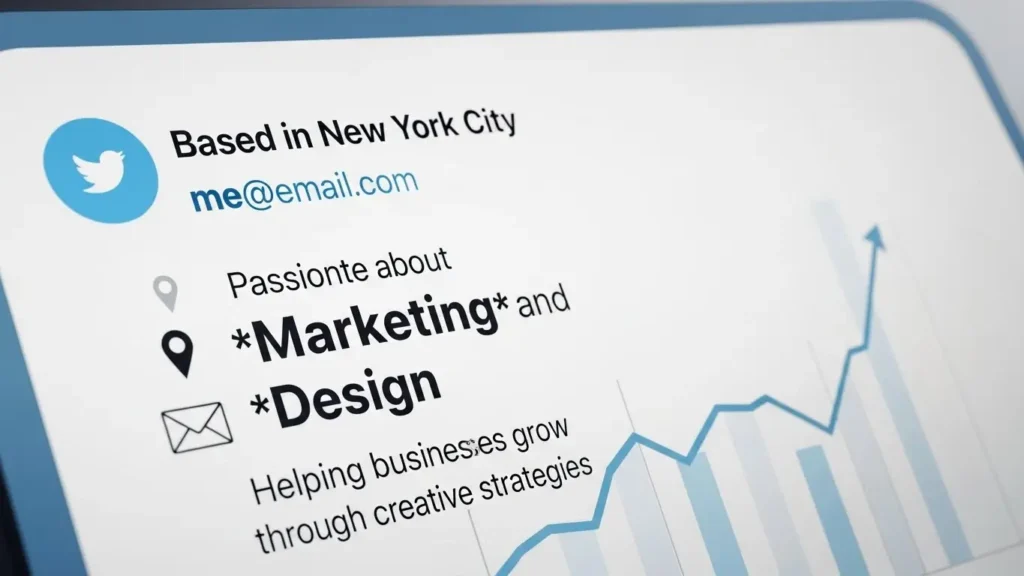
Twitter Schriftart ändern: So pimpen Sie Ihre X Bio für mehr Reichweite auf
Eine einzigartige Twitter Schriftart ist oft der entscheidende Faktor, der einen zufälligen Besucher dazu bringt, auf den “Folgen”-Button zu klicken oder weiterzuscrollen.
Wir kennen das alle: Man scrollt durch X (ehemals Twitter) und sieht hunderte von Profilen, die alle gleich aussehen. Standard-Text, Standard-Formatierung, Langeweile. Wenn Sie Ihre persönliche Marke oder Ihr Unternehmen auf dieser Plattform ernst nehmen, können Sie es sich nicht leisten, im Hintergrundrauschen unterzugehen.
In diesem Artikel zeige ich Ihnen als Experte für digitales Branding, wie Sie visuelle Akzente setzen. Wir gehen weg vom Standard und hin zu einem Profil, das Charakter zeigt. Keine Sorge, Sie müssen kein Designer sein. Es ist einfacher, als Sie denken.
Warum der Standard-Look Ihr Wachstum bremst
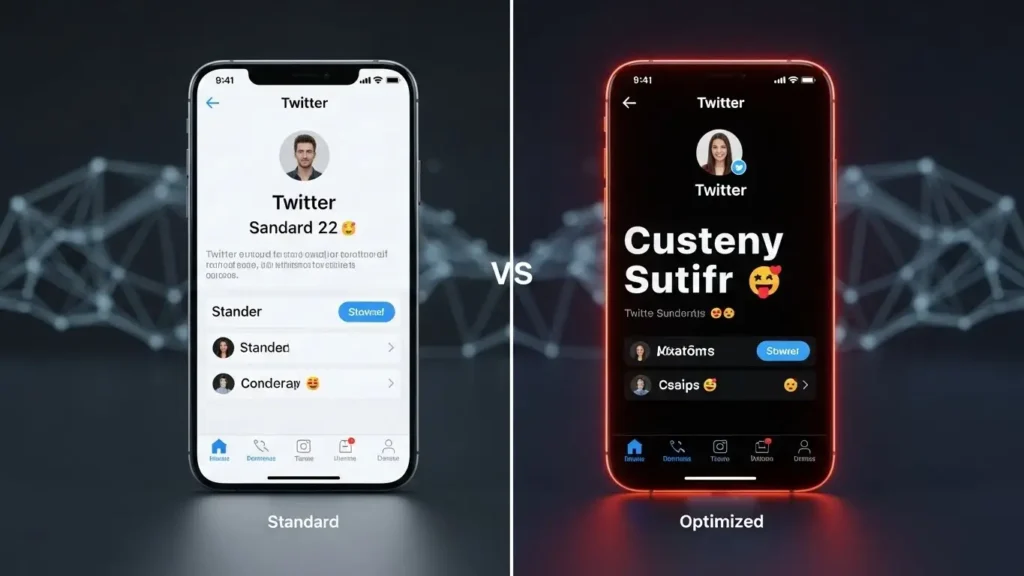
Haben Sie sich schon einmal gefragt, warum manche Accounts förmlich aus dem Bildschirm springen? Es liegt oft nicht nur am Inhalt, sondern an der Präsentation.
Die Standard-Schriftart von X, Chirp, ist funktional und gut lesbar. Das ist großartig für lange Threads, aber tödlich für Ihre Bio. Ihre Biografie ist Ihre Visitenkarte. Sie haben nur wenige Sekunden Zeit, um Interesse zu wecken.
Das Problem:
Wenn alles gleich aussieht, schaltet das menschliche Gehirn auf Autopilot. Wir überfliegen Texte, ohne sie wirklich wahrzunehmen.
Die Lösung:
Ein visueller “Stolperstein”. Durch den Einsatz spezieller Unicode-Zeichen brechen Sie das gewohnte Muster auf. Das Auge des Betrachters bleibt hängen. Genau diesen Moment der Aufmerksamkeit brauchen Sie, um Ihre Botschaft zu vermitteln.
Hier sind die klaren Vorteile einer angepassten Typografie:
- Sofortige Differenzierung: Sie heben sich von 99% der Nutzer ab.
- Markenidentität: Verspielte Schriften wirken kreativ, Serifenschriften seriös, Fettschrift autoritär.
- Struktur: Sie können wichtige Schlüsselwörter in Ihrer Bio fetten, um den Blick zu lenken.
Die richtige Twitter Schriftart für Ihre Marke finden
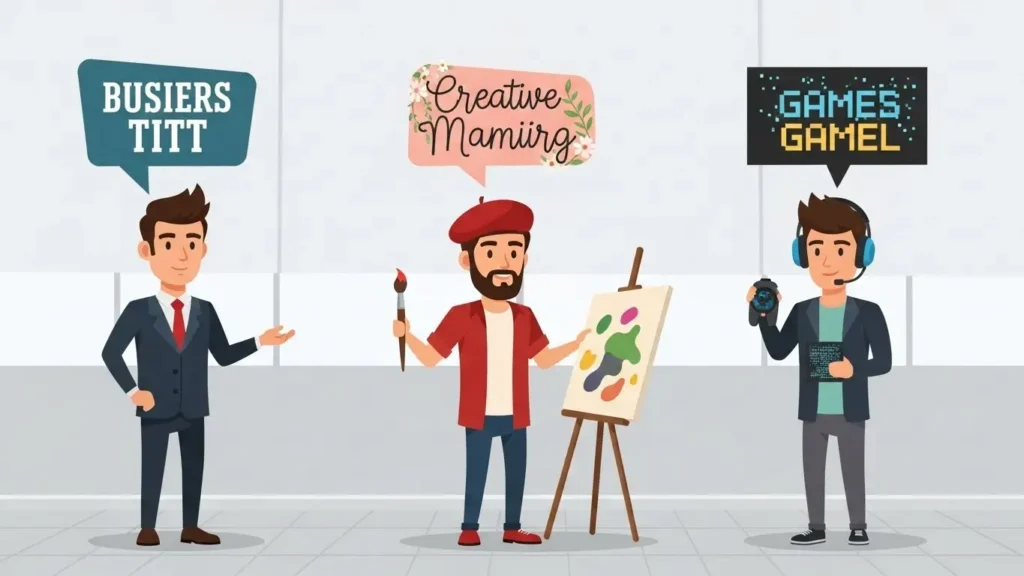
Nicht jede Schrift passt zu jedem Zweck. Bevor wir technisch werden, müssen wir strategisch denken. Die Wahl der Twitter Schriftart sollte immer Ihre Persönlichkeit oder Ihre Unternehmenswerte widerspiegeln.
Ein Finanzberater, der eine verschnörkelte Schreibschrift nutzt? Eher unglaubwürdig. Ein Künstler, der alles in strenger Monospace-Schrift hält? Vielleicht zu kühl.
Kategorie 1: Seriosität und Klarheit
Wenn Sie als Experte wahrgenommen werden wollen, empfehle ich fette Sans-Serif-Schriften oder kursiven Text. Diese Varianten sind gut lesbar und wirken professionell. Nutzen Sie Fettdruck gezielt für Keywords wie “SEO Experte”, “Autor” oder “Gründer”.
Kategorie 2: Kreativität und Lifestyle
Für Influencer, Gamer oder kreative Köpfe darf es ausgefallener sein. Hier funktionieren Schreibschriften (Script Fonts) oder Zeichen im “Bubble”-Stil hervorragend.
- Tipp: Weniger ist mehr. Schreiben Sie nicht Ihre gesamte Bio in einer schwer lesbaren gotischen Schrift. Nutzen Sie diese Effekte als Highlight für Ihren Namen oder Ihr Motto.
Schritt-für-Schritt: So ändern Sie Ihre Bio
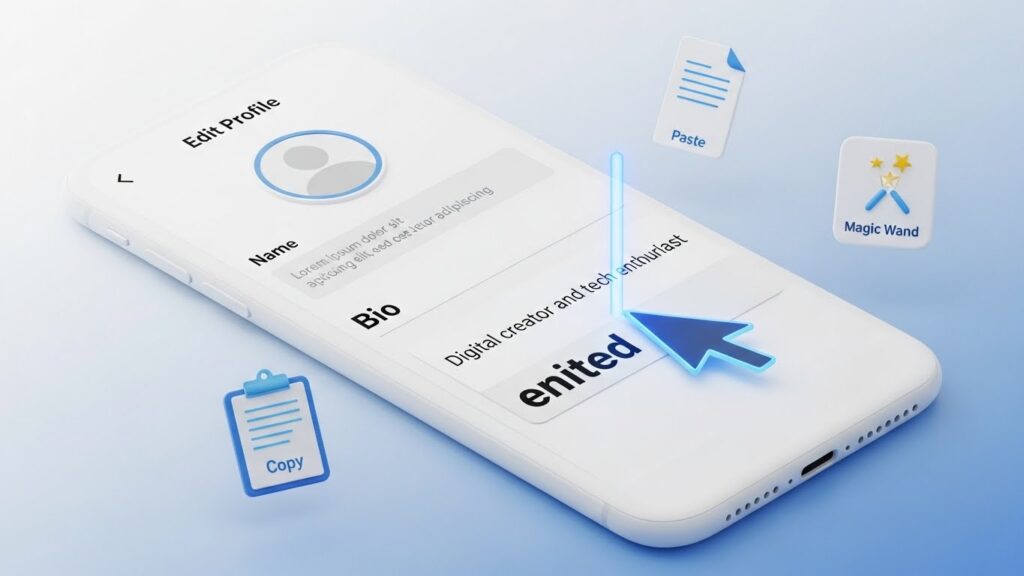
Jetzt wird es praktisch. Viele Nutzer glauben fälschlicherweise, dass man spezielle Software installieren muss. Das ist nicht der Fall. Wir nutzen sogenannte Unicode-Generatoren. Diese wandeln Ihren normalen Text in spezielle Symbole um, die wie andere Schriftarten aussehen, aber technisch gesehen “Bilder” oder Symbole sind, die jeder Browser darstellen kann.
Der Prozess im Detail:
- Text vorbereiten: Schreiben Sie Ihre Bio zuerst in einer normalen Notiz-App vor. Überlegen Sie genau, welche Wörter hervorgehoben werden sollen.
- Generator nutzen: Kopieren Sie Ihren Text. Wenn Sie auch auf anderen Plattformen aktiv sind, lohnt sich ein Blick auf spezialisierte Tools wie den Instagram Schrift Generator, da diese oft auch perfekt für Twitter funktionieren.
- Style auswählen: Fügen Sie den Text in den Generator ein. Sie sehen nun eine Liste mit verschiedenen Stilen.
- Kopieren und Einfügen: Wählen Sie Ihren Favoriten, kopieren Sie ihn und gehen Sie zu Ihrem X-Profil.
- Profil bearbeiten: Klicken Sie auf “Profil bearbeiten”, fügen Sie den neuen Text in das Bio-Feld ein und speichern Sie.
Wichtiger Hinweis zur Barrierefreiheit: Screenreader (Vorlese-Software für Sehbehinderte) haben oft Probleme mit diesen Unicode-Schriften. Nutzen Sie ausgefallene Schriften daher niemals für lebenswichtige Informationen wie Kontakt-E-Mails oder rechtliche Hinweise. Beschränken Sie es auf Namen oder Slogans.
Probieren Sie es jetzt aus. Wählen Sie eine Twitter Schriftart, die zu Ihnen passt, aktualisieren Sie Ihre Bio und beobachten Sie die Reaktion Ihrer Community. In der lauten Welt von Social Media gewinnt nicht derjenige, der am lautesten schreit, sondern derjenige, der am besten im Gedächtnis bleibt.